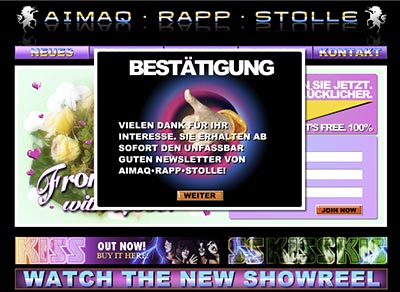
Aimaq·Rapp·Stolle: mutige WebsiteEiner unserer treuesten Kunden – Aimaq·Rapp·Stolle –
hat seine Website überarbeitet. Wie Page-online meldet, informierte AD Christian Feldhusen heute
die Branche per Mail über den Relaunch: »Die neue site unserer
agentur, aimaq rapp stolle, ist online. nichts ungewöhnliches...
eigentlich. aber irgendwie entspricht sie nicht wirklich den momentanen
standards und sie sorgt positiv wie negativ in einschlägigen kreisen fuer
gesprächsstoff.« Recht hat er
![]() Die Berliner Agentur ars setzt auf Trash-Design: gruselige Typografie, nervige
Spielereien und Animationen, Farbverläufe bis der Arzt kommt, jeder Klick
eine Beleidigungen fürs Auge. Gefälschte Webebanner, zum Beispiel
für eine Kiss-CD, führen zur Amazon-Website. Ein
Berlin-Maskottchen-Bär und ein Cheeseburger mit Augen überbrücken
die Wartezeiten. Damit reiht sich Aimaq·Rapp·Stolle in die Liga der
mutigsten Design-Vorreiter Europas ein, angeführt von KesselsKramer (Amsterdam, Holland) und dem Anglerheim Glindow
(Werder, Brandenburg). Wie sagte bereits die Kung-Fu-Legende Inuyasha: Genies
springen in ihren Schatten und nicht drüber.